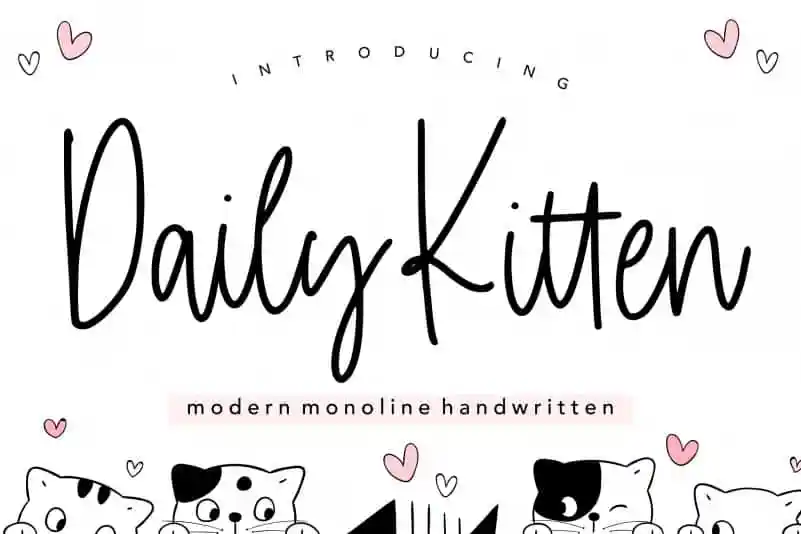
Daily Kitten Handwritten Font – Download Grátis
A fonte Daily Kitten Handwritten é perfeita para um vasto leque de projetos digitais. Seja para adicionar um toque criativo aos pacotes de produtos, criar uma identidade visual memorável para seu projeto de marca, tornar sua revista mais atraente ou até mesmo dar o tom certo em suas postagens no Instagram, Facebook ou TikTok. Ela é especialmente adequada para expressar as palavras em destaque sobre um fundo neutro, seja no contexto de uma festa romântica ou em qualquer outra situação em que você deseja adicionar um elemento delicado e encantador à sua tela digital. A Daily Kitten Handwritten se adapta perfeitamente a várias finalidades, tornando-a uma opção indispensável para aqueles designers gráficos buscando adicionar um toque de personalidade ao seu trabalho. Não importa qual seja o projeto ou plataforma que você está trabalhando, esta fonte tem o potencial de transformar qualquer visual digital em algo único e encantador.